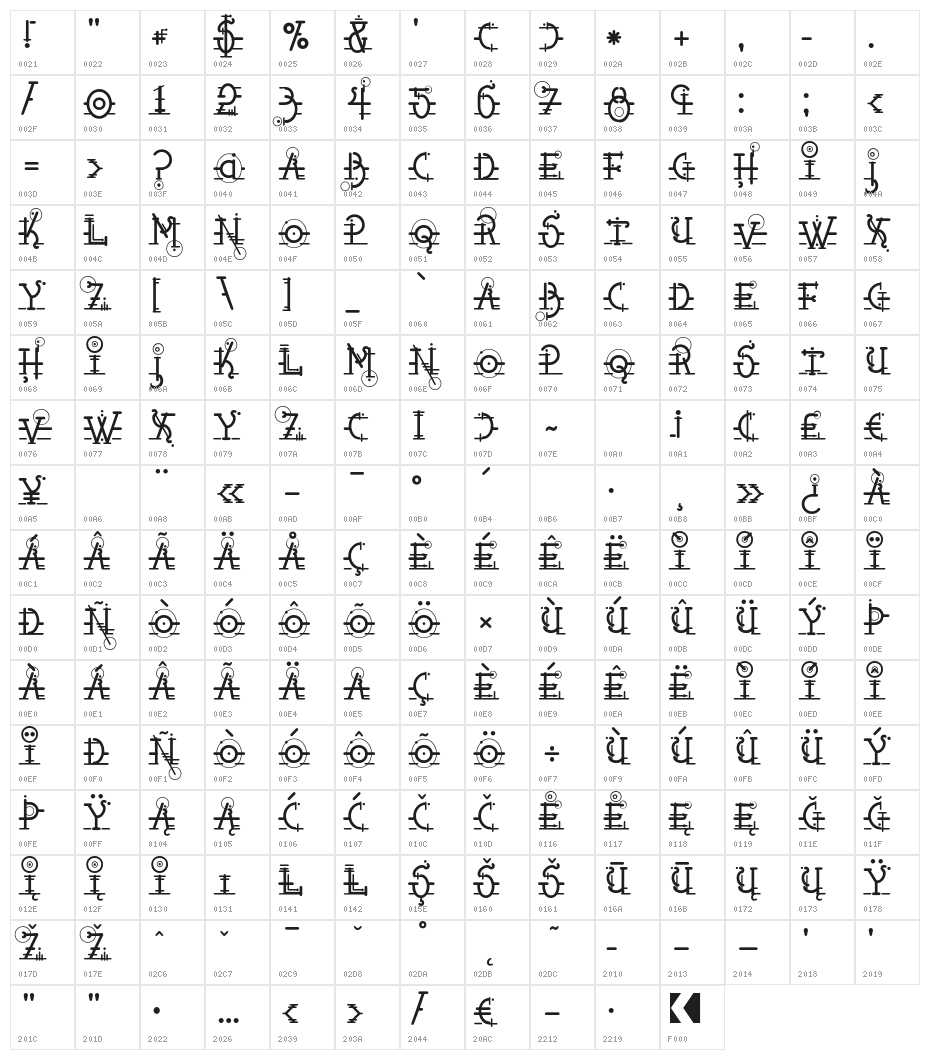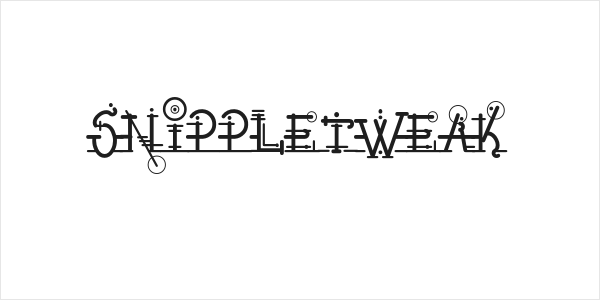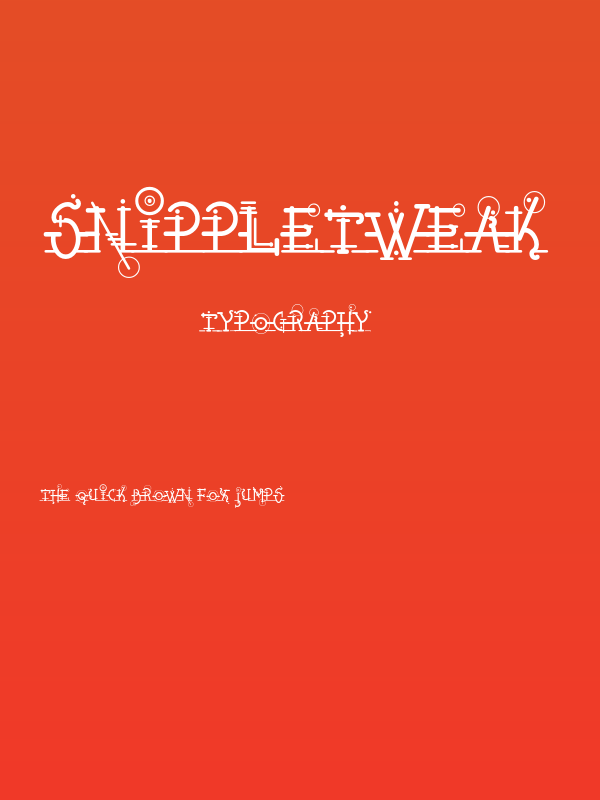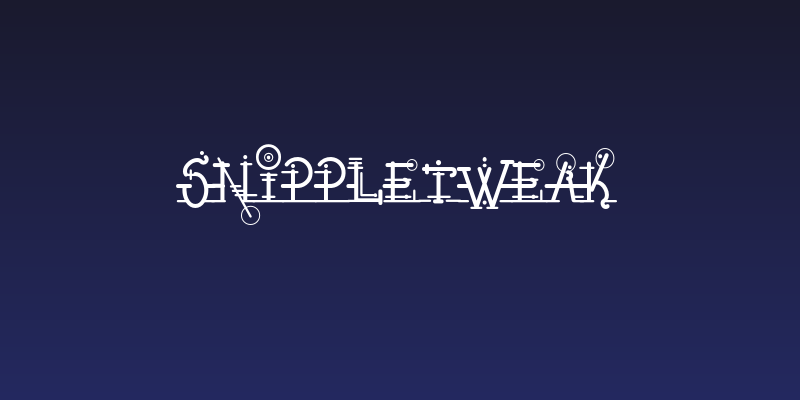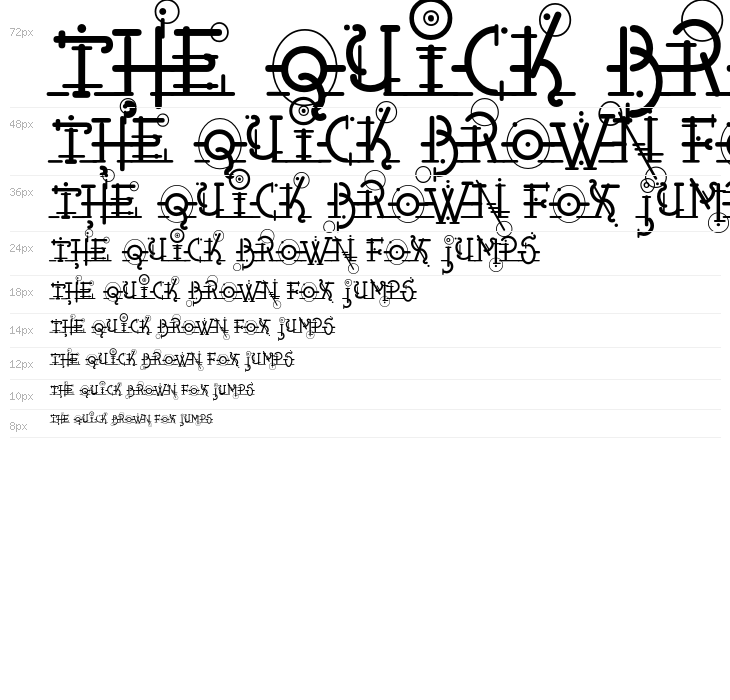
Snippletweak Font
| Gesamtstil | Futuristic, Avant-garde |
| Anwendungsfall | Logos, Posters, Album covers |
| Vorgeschlagene Projekte | Ideal for use in artistic projects, sci-fi themed designs, posters, album covers, and branding that seeks a unique and modern edge. |